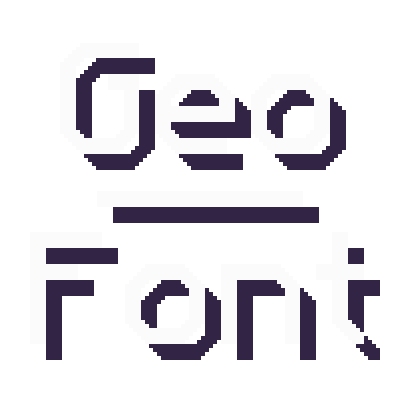
Geometric Font Legacy
Чёткая HD-переработка стандартного шрифта Mojangles для Майнкрафт. Подходит для любых разрешений, но требует правильного масштаба GUI.
Geometric Font Legacy - это ресурспак для Майнкрафт, который заменяет стандартный шрифт Mojangles на более острый и чистый в высоком разрешении. Если вам надоели размытые буквы при масштабировании интерфейса, этот вариант решит проблему.
Шрифт перерисован в Full HD, но из-за того, как игра отображает GUI, текстуры высокого разрешения выглядят неровно, если масштаб интерфейса не совпадает с тем, на который рассчитан ресурспак. По умолчанию загрузка идёт для масштаба 4, но если вы используете другой, обязательно загляните в последний релиз и скачайте версию под свой масштаб - так картинка будет идеально чёткой.
Автор переработал концепцию в Geometric Font 2 - это OpenType-шрифт с новыми возможностями и лучшей согласованностью. А для любителей футуристичного стиля есть Geometric Font Edge - научно-фантастический вариант. Оба доступны по ссылкам.
HD-шрифтов для Майнкрафт много, но большинство из них слишком мягкие или не подходят под ванильный стиль. Geometric Font Legacy специально заточен под резкие, чёткие контуры - именно так, как выглядит стандартный Mojangles, но без пиксельной размытости. Подходит тем, кто ценит аккуратный интерфейс и играет на высоких разрешениях.